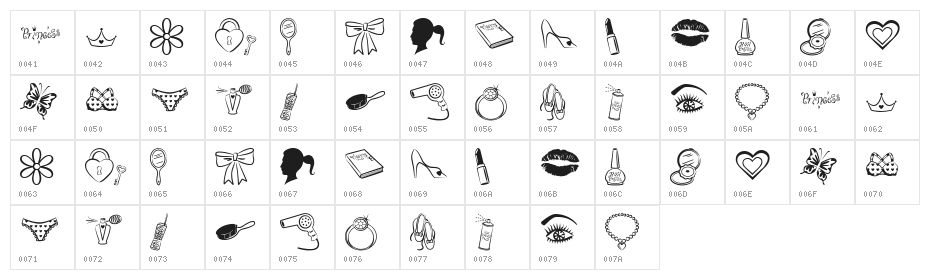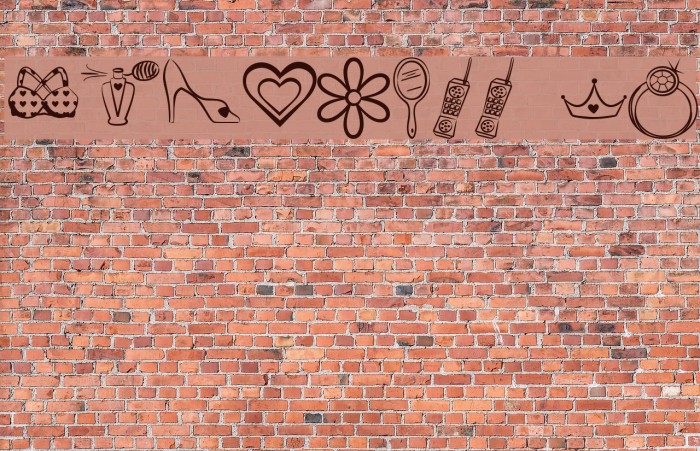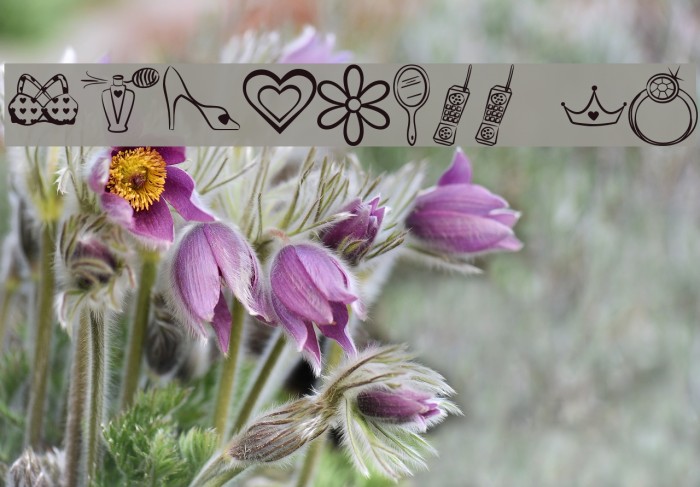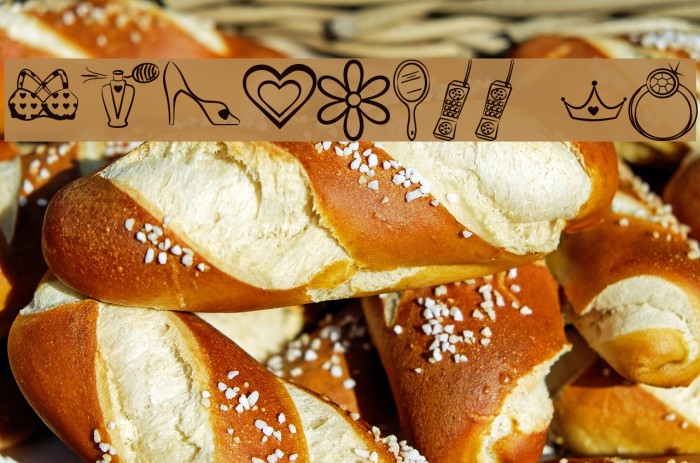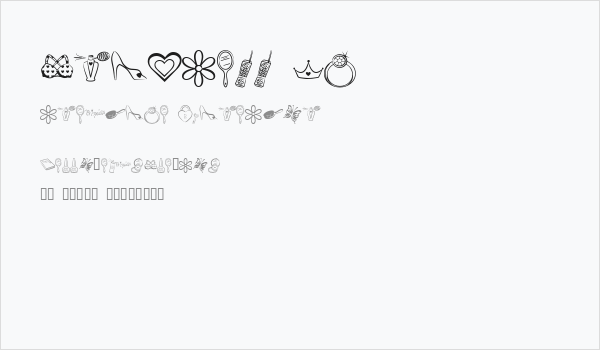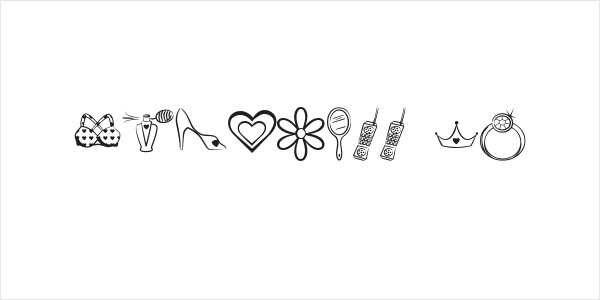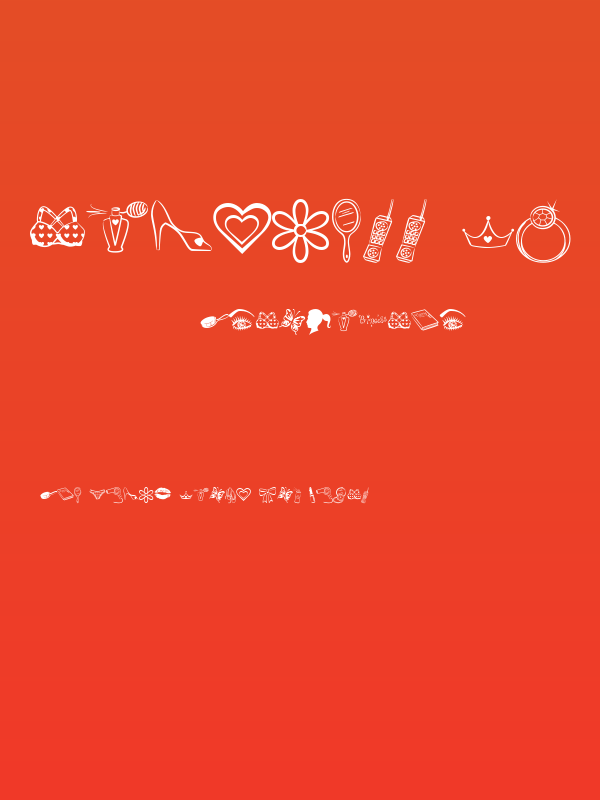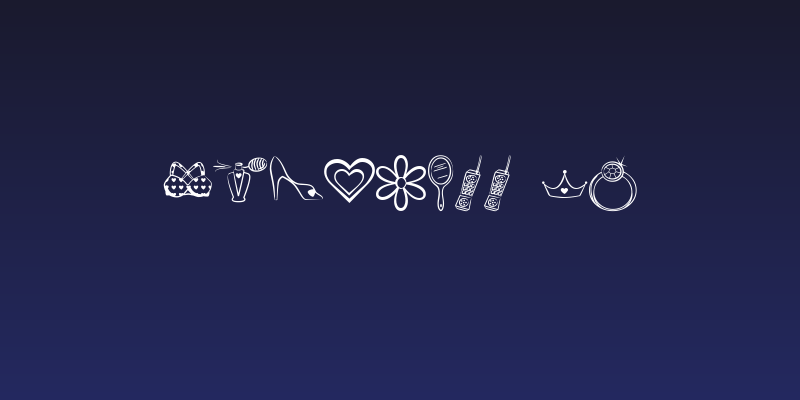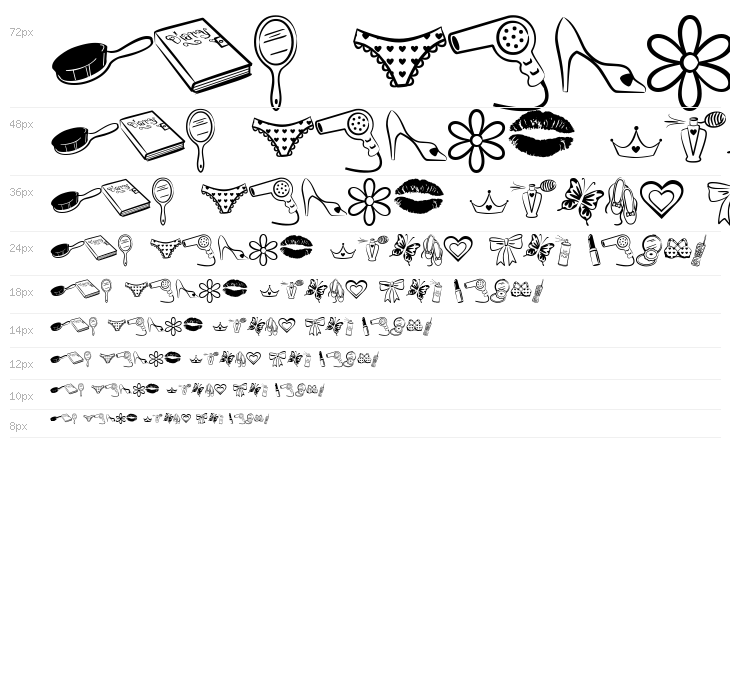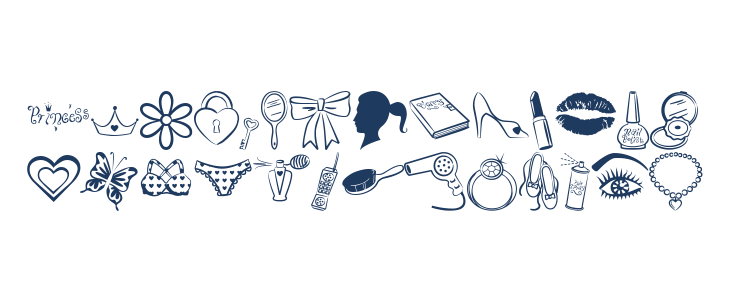
Princess BV Font
| Caso de uso | Decorative elements for creative projects. |
| Proyectos propuestos | Ideal for use in scrapbooking, greeting cards, fashion design, or any project that could benefit from a playful and stylish theme. |